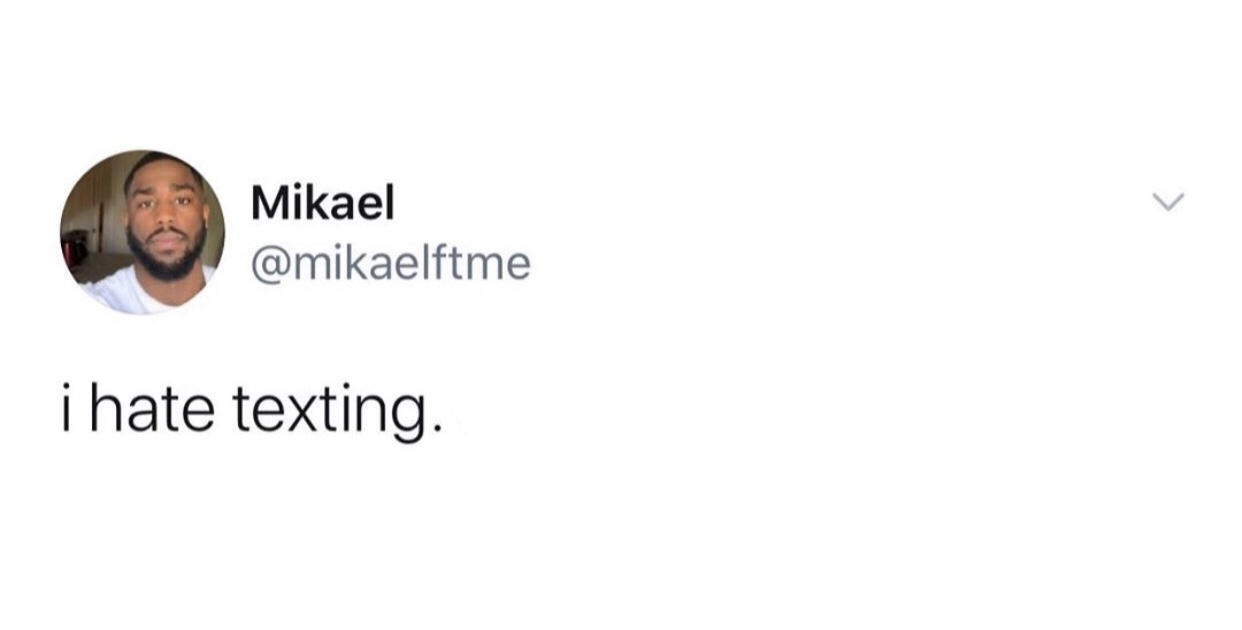
Bu hangi font ?
- 17-10-2020, 14:30:05Selam, görsel font bulma sitelerinden sonuç elde edemedim, yardım için şimdiden teşekkürler.
- 17-10-2020, 15:42:48a ve g aynısı değiloxopage adlı üyeden alıntı: mesajı görüntüle
- 17-10-2020, 15:44:13font yaygınlığı görselden kaynaklı. o nedenle farklı görünüyor...yalinyalniz adlı üyeden alıntı: mesajı görüntüle
- 17-10-2020, 15:44:55a'nın kuyruğu farklıoxopage adlı üyeden alıntı: mesajı görüntüle
- 17-10-2020, 15:45:50Şimdi tekrar baktım farklıymış, büyük puntoda belli oldu.yalinyalniz adlı üyeden alıntı: mesajı görüntüle